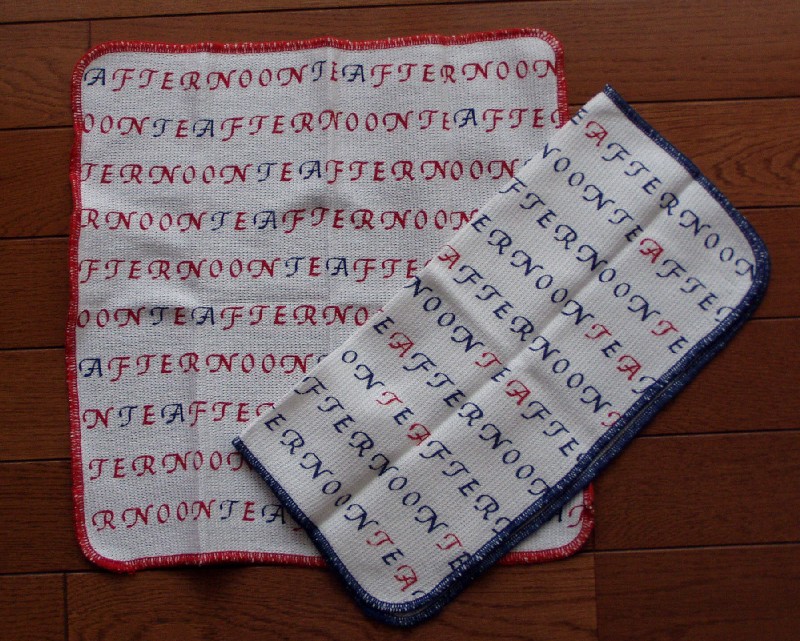
アルファベットのふきん
先日、友人とアフタヌーンティーで優雅にお茶を楽しみました。午後のひととき、ゆっくりと(ねばっって…?)お喋りしながらスコーンとお茶をいただくのはこの上ない贅沢ですね…。
スタバでのお茶がカジュアルな感じだとするとアフタヌーンティーは少しおしゃまな感じでしょうか…。
自由が丘のお店は3階でお食事とお茶ができ、1階、2階がショップになっています。帰り際に2階に寄り道。そこで見つけたのが、籐のかごにすました顔で並んでいたアルファベット柄のふきんです。少し重たい感じの書体ではありますが、何か可愛くて…つい購入してしまいました。いけない…また文字好きの癖が出てしまいました。
いつもは可愛いものにはあまり興味を示さない友人も「ほれ、ほれ…」と言う私の見せびらかしに、つい買ってしまったのでした〜。